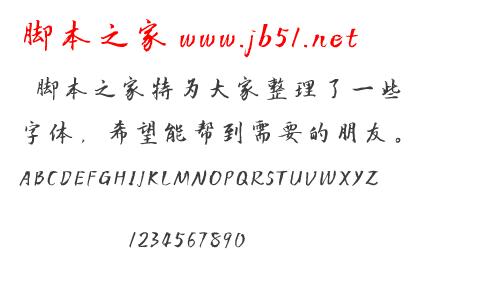
方正墨顏體是一款書法字體,字形大小疏密有致,結(jié)體秀美,倚側(cè)秀逸,整體作品氣韻生動,形神兼?zhèn)?。適用于文藝類的書刊、品牌廣告和產(chǎn)品包裝設(shè)計,現(xiàn)代詩歌、短文排版,文化商業(yè)類宣傳設(shè)計,以及社交網(wǎng)絡(luò)的個性化用字。歡迎喜歡這款字體的朋友下載收藏。